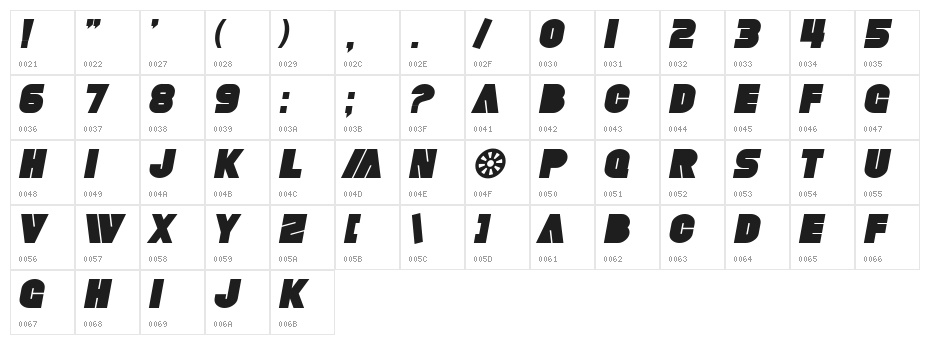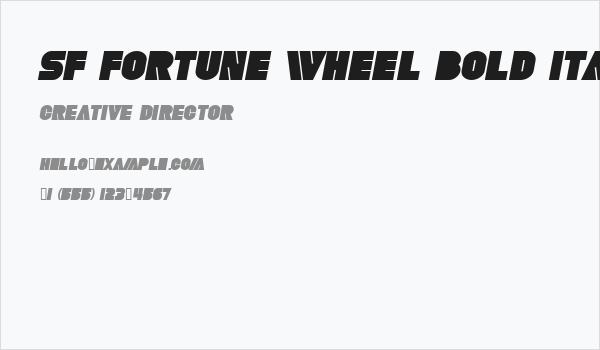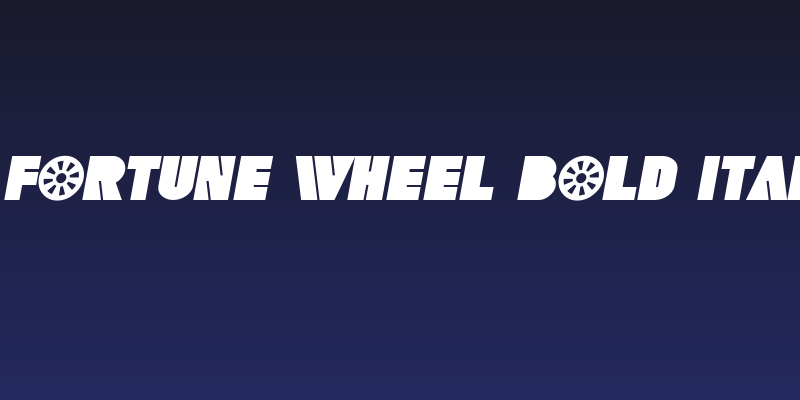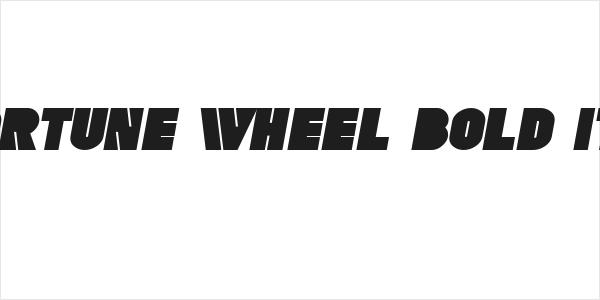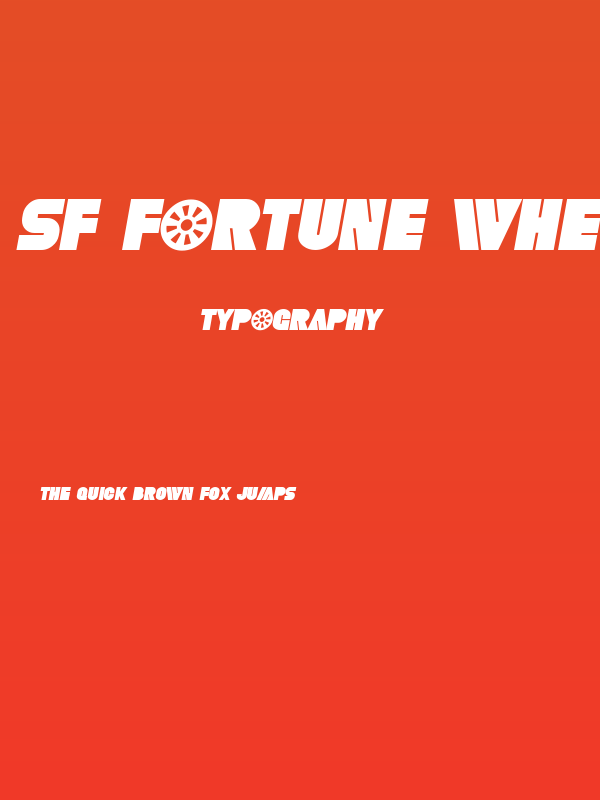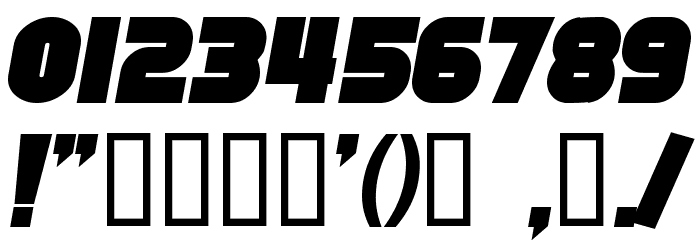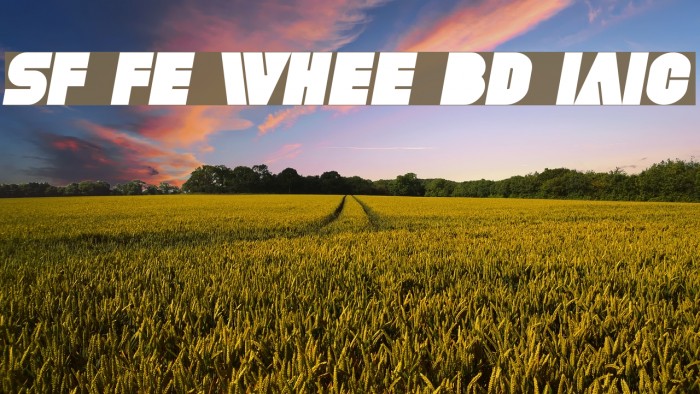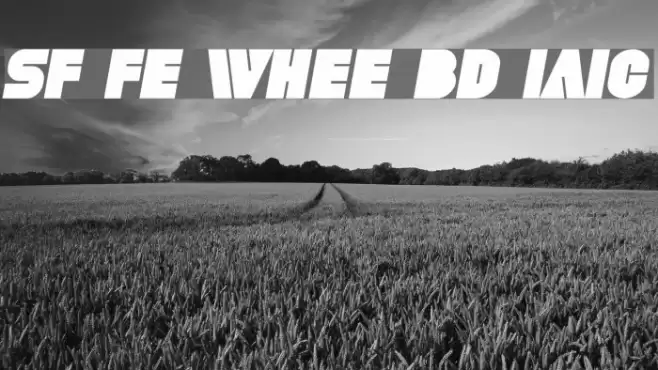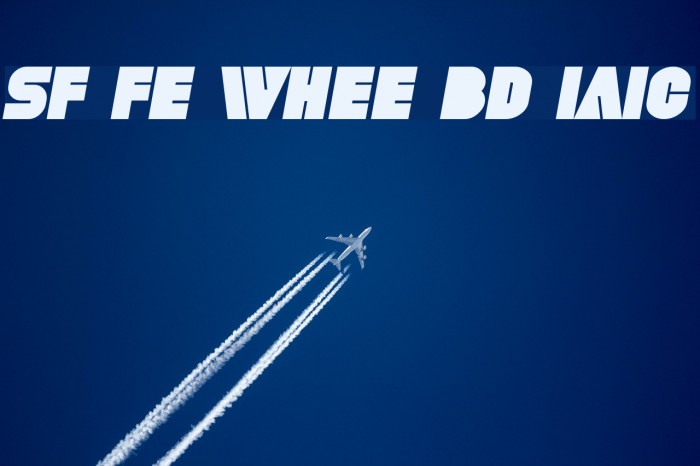
SF Fortune Wheel Bold Italic Font
| Vorgeschlagene Projekte | Ideal for branding, advertising, poster design, and any project needing a modern, dynamic typeface. |